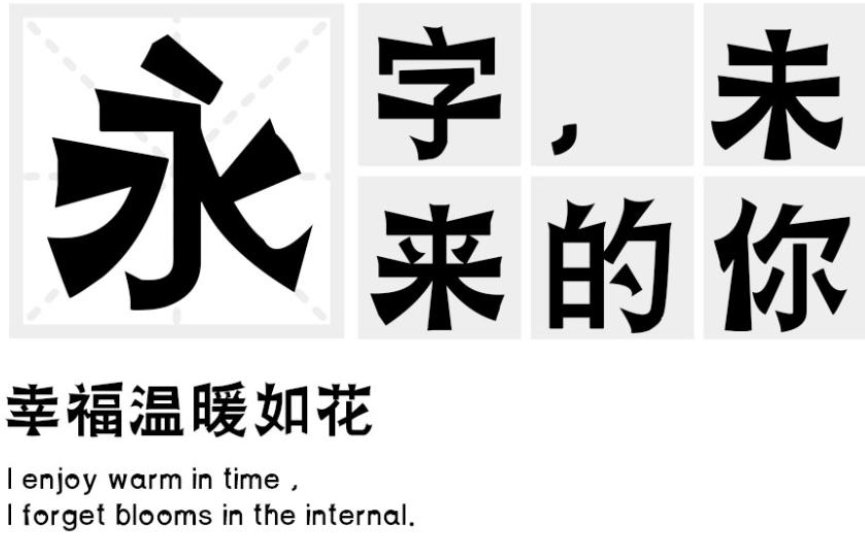
仿爨宝子发布
字体名称:仿爨宝子
字体类别: 书法字体
仿爨宝子简介:根据《爨宝子碑》的字形创作而来,作者以楷书新体之法强为旧体隶书之体,只能状其仿佛,非楷非隶,当今不谙隶法的学书者开始写隶书时,也往往以楷入隶,字形与此相类。适合应用于艺术设计、平面宣传、包装印刷、图形设计、网页设计、书法字帖等领域。